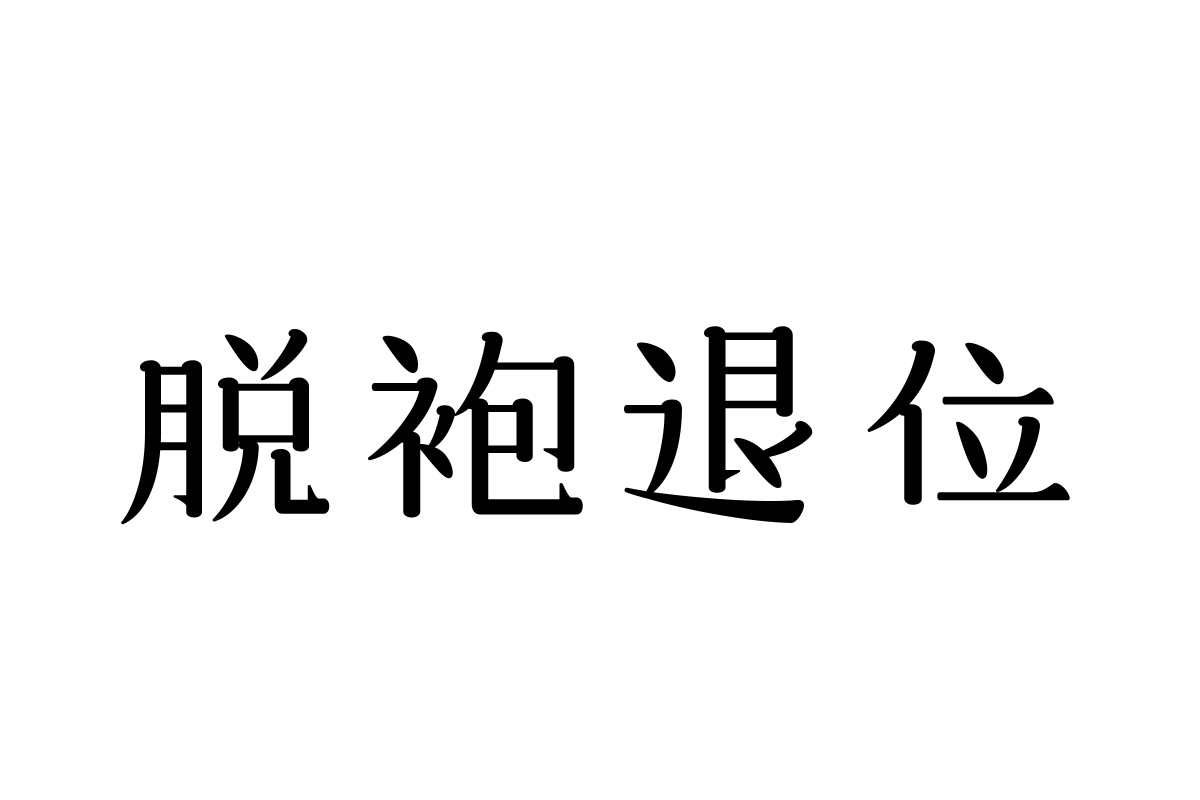
三极悠闲宋是一款具有现代感的中文字体,由三极科技推出。这款字体的设计灵感来源于传统的宋体,但又融入了一些现代元素,使其更加时尚和易读。
三极悠闲宋的特点如下:
1. 字形清晰:这款字体的字形规整,笔画流畅,易于阅读和书写。无论是在印刷品还是电子屏幕上,都能展现出良好的视觉效果。
2. 现代感强:虽然继承了宋体的传统,但三极悠闲宋在细节上进行了创新,如增加了一些现代设计元素,使其更具时尚感。
3. 适应性强:这款字体适用于各种场景,包括书籍、杂志、报纸、广告、网页等。无论是正式的文件还是非正式的社交媒体内容,都能完美匹配。
总的来说,三极悠闲宋是一款适合现代办公和日常生活的优雅字体,既保留了传统韵味,又不失时尚气息。